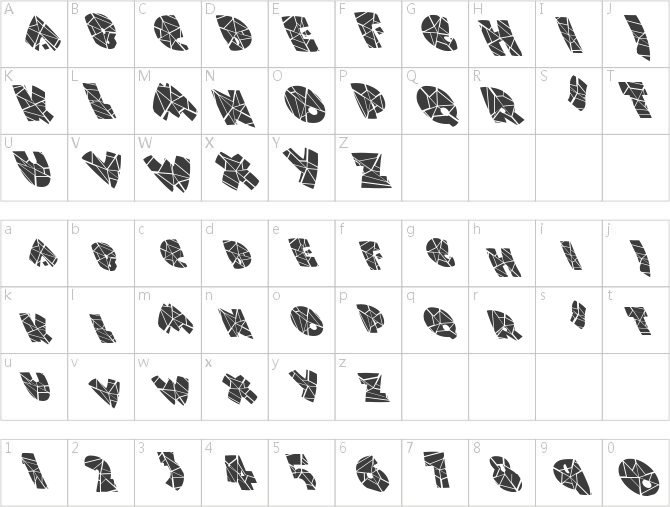
FZ JAZZY 9 CRACKED LEFTY
FZ JAZZY 9 CRACKED LEFTY介绍
FZ JAZZY 9 CRACKED LEFTY字体字库是一款让人赏心悦目、百看不厌的英文字体,适合各类广告和产品包装设计应用,字体大小0.11MB,格式为ttf字体,上传用户是青柠檬,作者/版权方为未知